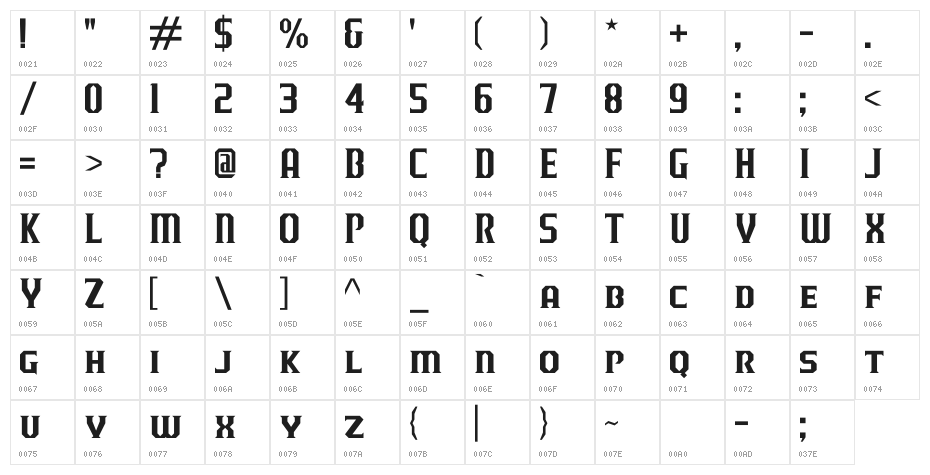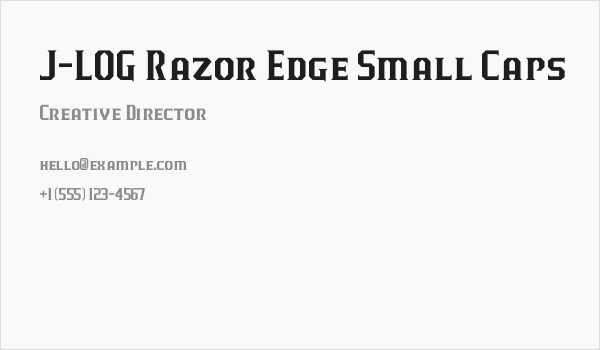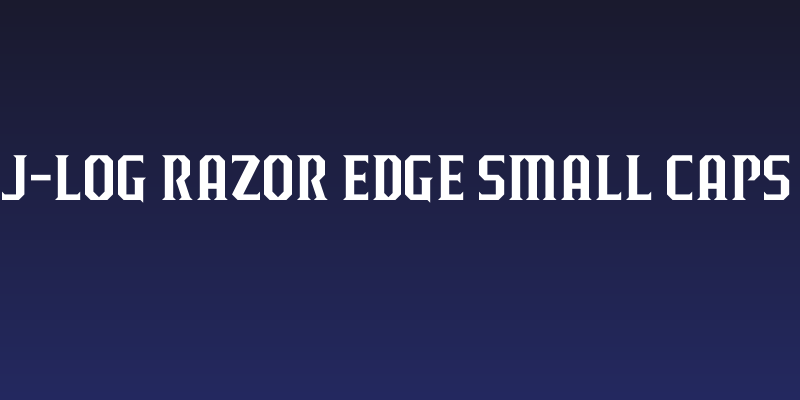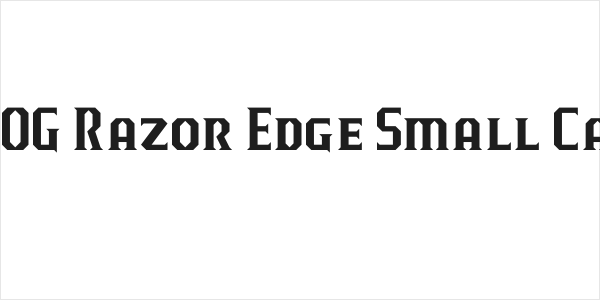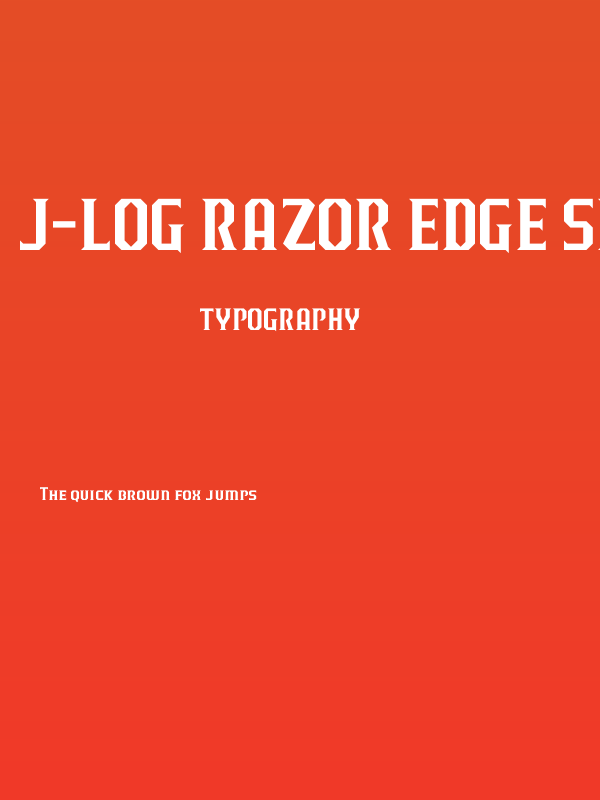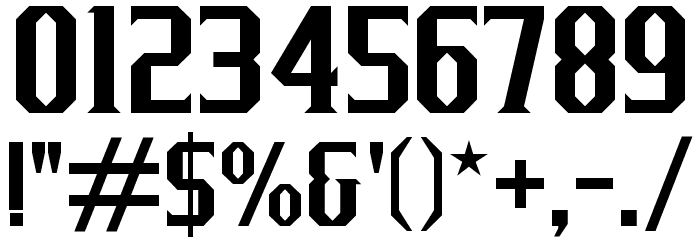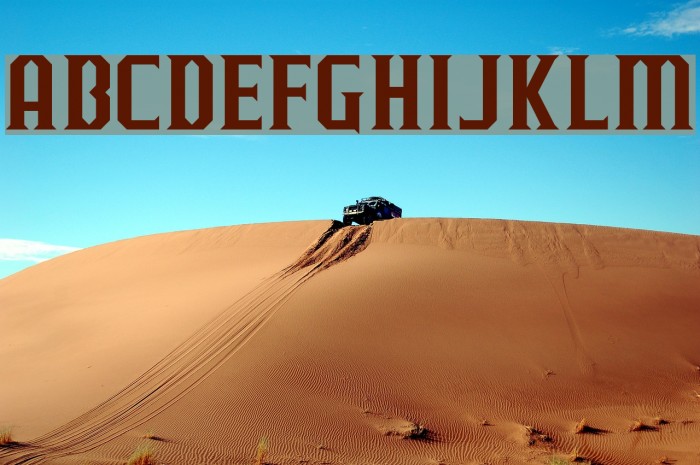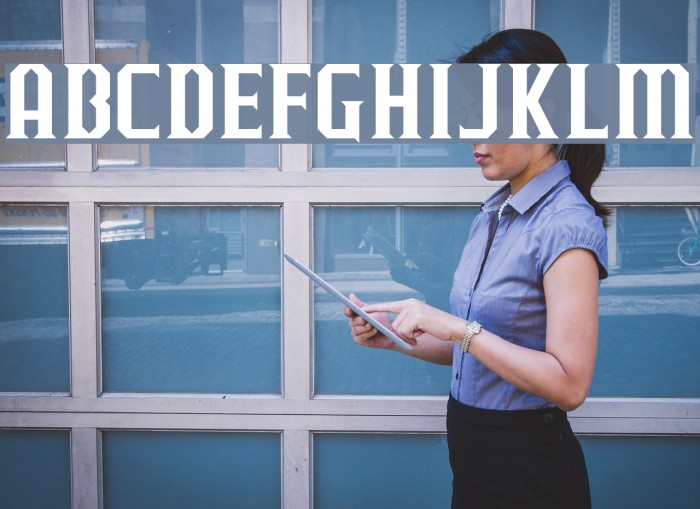
J-LOG Razor Edge Small Caps Font
John Ocasio - www.ffonts.net/myfonts/jlog3000/
| Рекомендуемые проекты | Ideal for branding, posters, album covers, and any project requiring a bold, eye-catching typeface. |